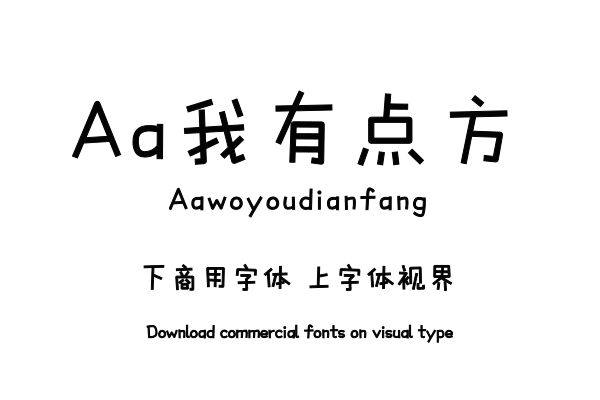
我有点方是一款手写风格的创意字体,字形略瘦高、方正,笔画光滑、简洁、利落。结构稳定,易读性良好。字体风格生动、呆萌,个性独特。作为标题正文均可,适用场景广泛。购买须知:“下载服务费”与“字体VIP”所获得字体 仅用于个人非商用, 商用请联系付费授权。本字体为电脑用字,手机没有root权限不支持直接手机换字(手机如何root,请自行百度搜索教程)。购买前请先 了解清楚后再付款 ,字体为虚拟产品无法回收 一旦购买不支持退款。